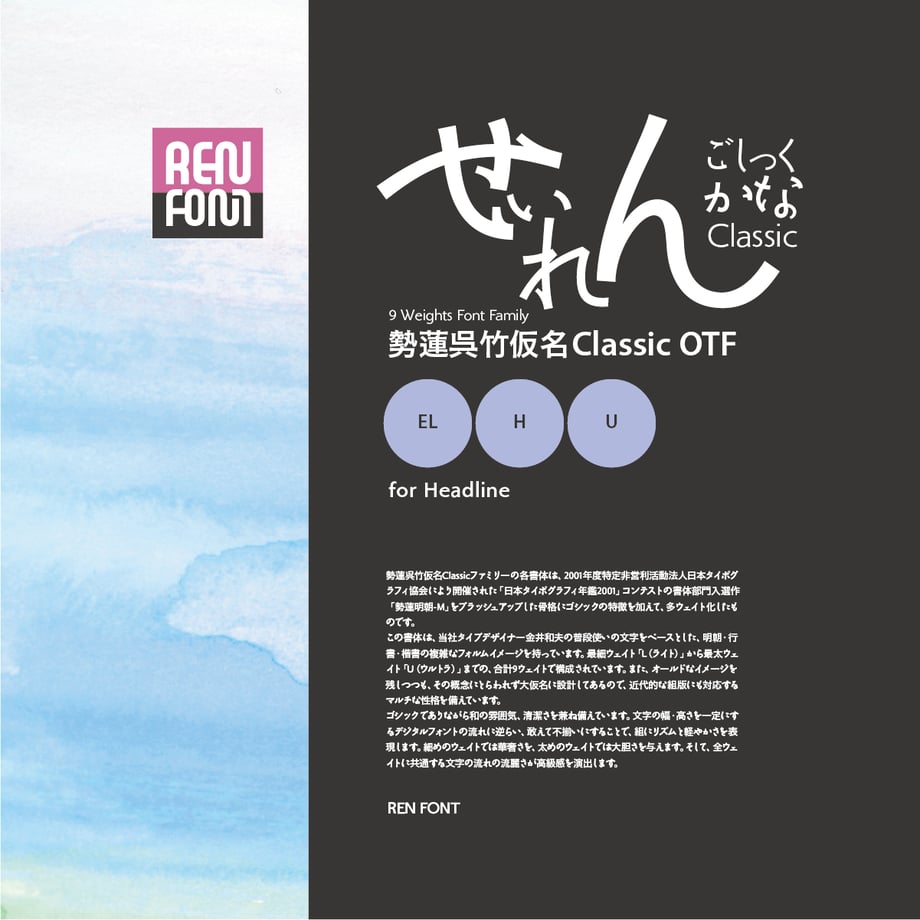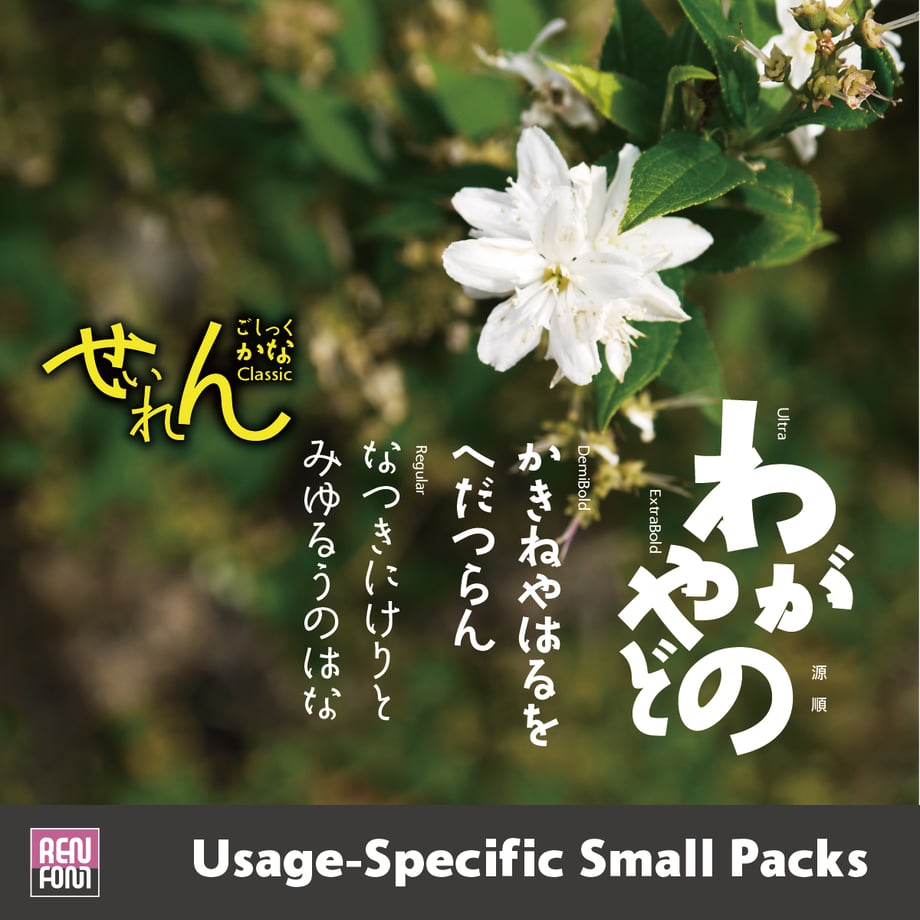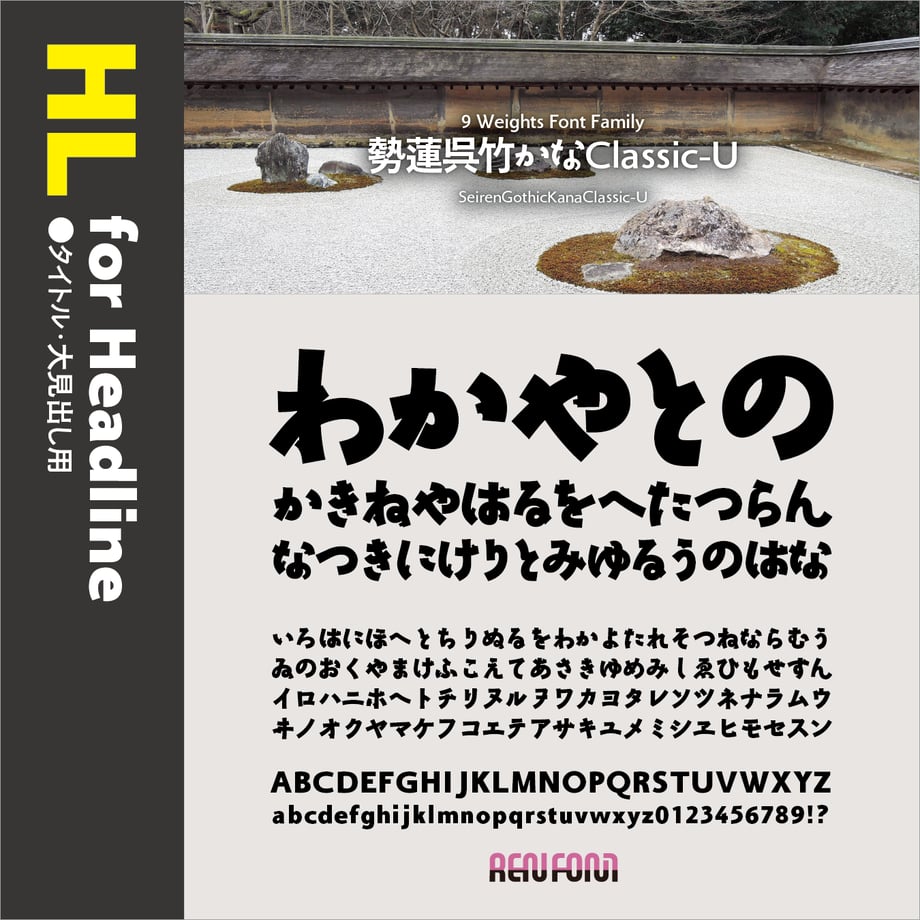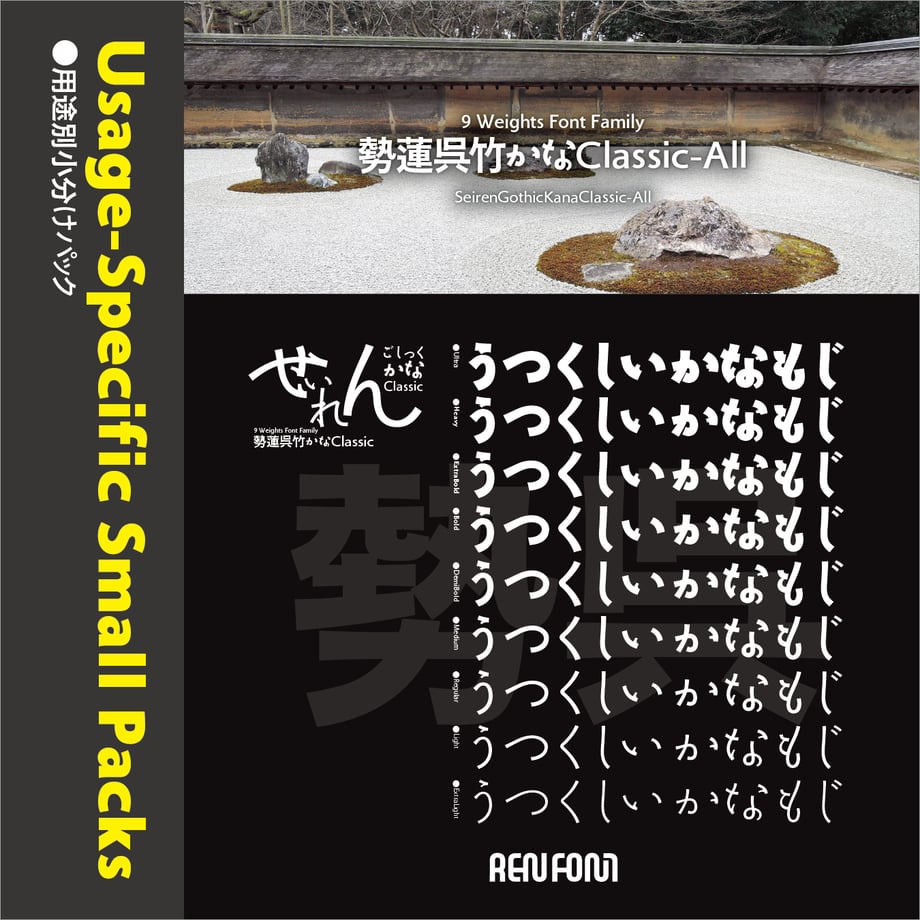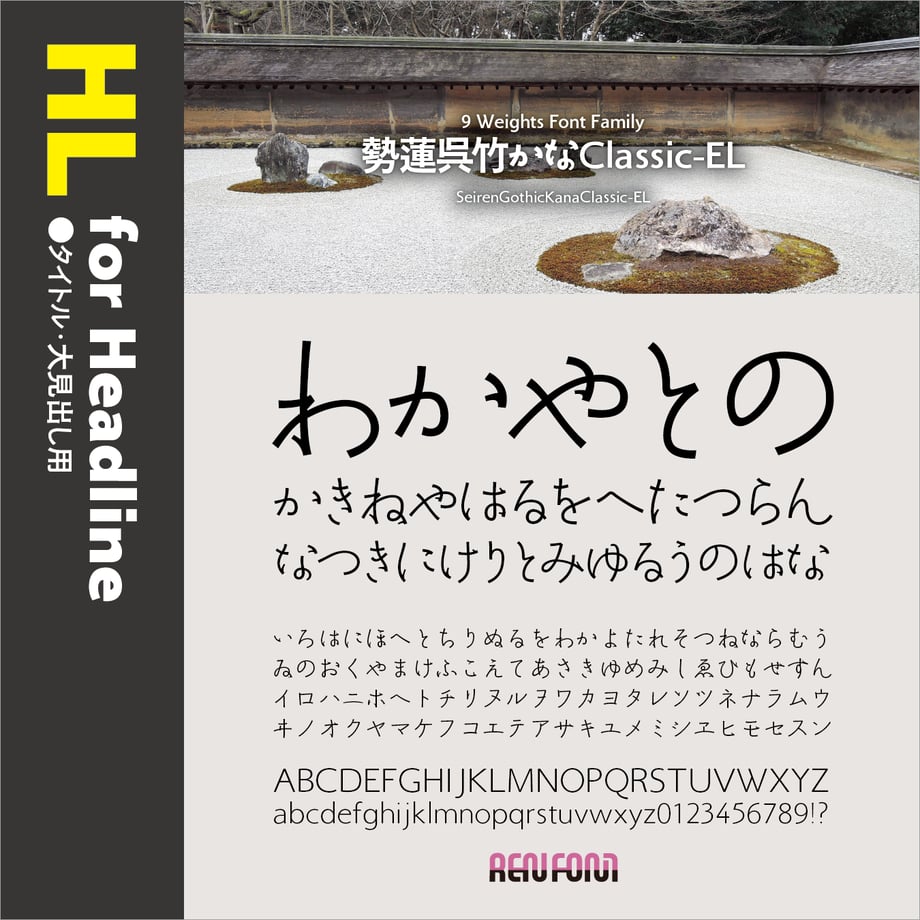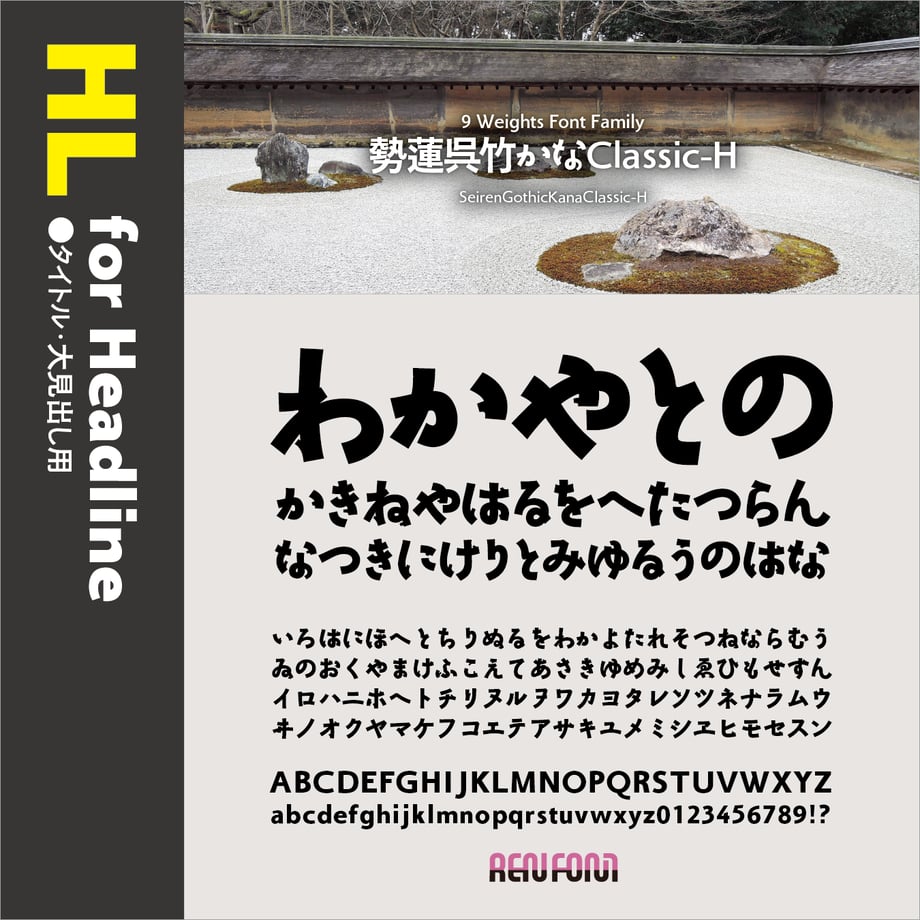
勢蓮呉竹仮名Classic-HL(タイトル・大見出し用)EL/H/U
ゴシックを感じさせない優雅さ
勢蓮呉竹仮名Classic 9ウェイトファミリー / OpenType
勢蓮呉竹仮名Classicファミリーの各書体は、2001年度特定非営利活動法人日本タイポグラフィ協会により開催された「日本タイポグラフィ年鑑2001」コンテストの書体部門入選作「勢蓮明朝-M」をブラッシュアップした骨格にゴシックの特徴を加えて、多ウェイト化したものです。
この書体は、当社タイプデザイナー金井和夫の普段使いの文字をベースとした、明朝・行書・楷書の複雑なフォルムイメージを持っています。最細ウェイト「L(ライト)」から最太ウェイト「U(ウルトラ)」までの、合計9ウェイトで構成されています。また、オールドなイメージを残しつつも、その概念にとらわれず大仮名に設計してあるので、近代的な組版にも対応するマルチな性格を備えています。
ゴシックでありながら和の雰囲気、清潔さを兼ね備えています。文字の幅・高さを一定にするデジタルフォントの流れに逆らい、敢えて不揃いにすることで、組にリズムと軽やかさを表現します。細めのウェイトでは華奢さを、太めのウェイトでは大胆さを与えます。そして、全ウェイトに共通する文字の流れの流麗さが高級感を演出します。
ゴシック体の形状を基本にしていますが、明朝・行書・楷書のイメージも含んでいます。
作者の普段使いの文字をアレンジしてあるので、ゴシック体のセオリーを外した筆勢も随所にあり、強い個性と主張を発揮します。
文字の高さや横幅がフォントの概念を覆すほどバラエティに富んでいるので、一文字ずつばらしてサイズに強弱をつけると、見出しとしてあたかも書道のような最大限の効果を得られます。また、本文組にも既存の漢字と組み合わせてよく調和します。
欧文・数字は、特徴の強い両仮名に合わせて独自にデザインしました。
格調高いMyriadに似た形状をしていますが、よりオールドな風合いの設計になっています。欧文書体としての単独使用にも十分に耐えうる、和文付嘱書体としては稀な、非常に高い完成度を持っています。